Материал обновлен в сентябре 2021 года. Proxima Nova, DIN, Futura и Brandon Grotesque – одни из самых популярных платных шрифтов в мире. Они используются в веб-дизайне, брендинге и печати. Для большинства дизайнеров эти шрифты недоступны из-за высокой стоимости. Предлагаем подборку из 11 шрифтов, которые являются бесплатной альтернативой популярным платным вариантам.
1. Montserrat вместо Proxima Nova
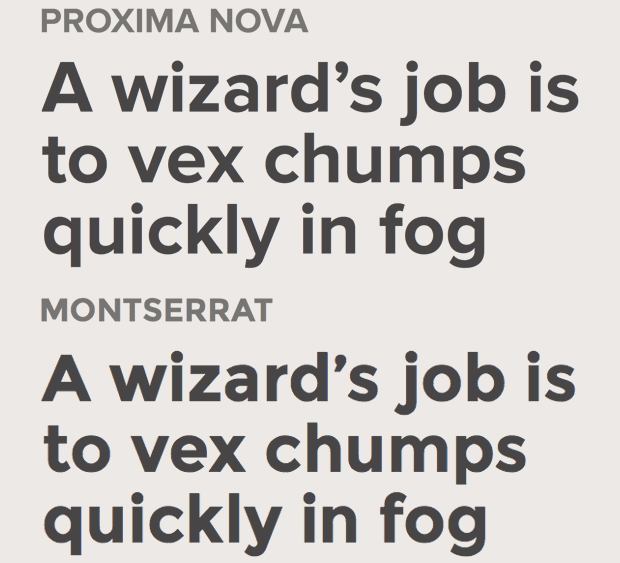
С момента своего релиза 10 лет назад шрифт Proxima Nova занял лидирующие позиции. Для тех, у кого нет этого шрифта, может подойти Montserrat – бесплатный геометрический шрифт с очень похожими характеристиками. Он хорошо смотрится в верхнем регистре (заглавными буквами).
2. Josefin Sans вместо Futura
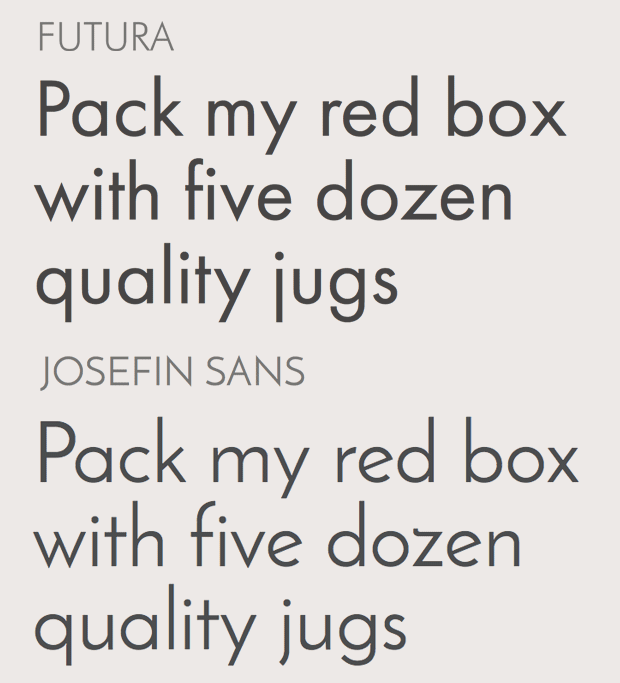
Futura – любимый геометрический шрифт каждого, кто знаком с его острыми углами. Как бесплатная альтернатива может подойти Josefin Sans – чистый геометрический шрифт. Формы символов этих шрифтов практически идентичны. Разница менее заметна при использовании верхнего регистра.
3. Roboto вместо FF DIN
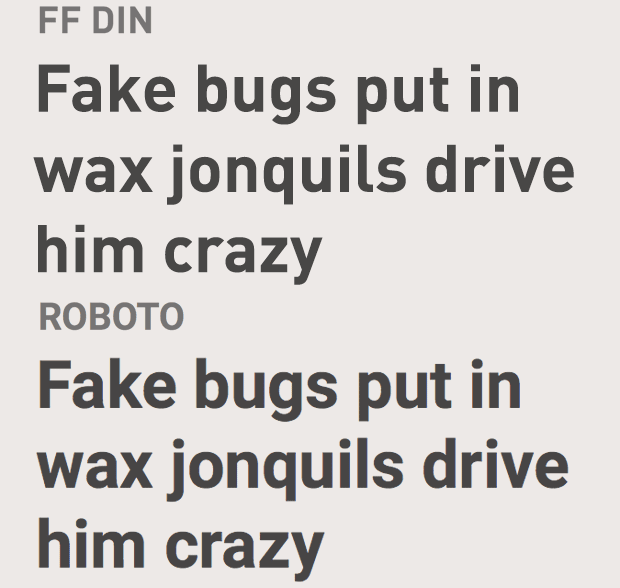
Roboto – лучшая альтернатива популярному шрифту FF DIN. Многие символы этих шрифтов совпадают как в нижнем, так и в верхнем регистре, а наличие стилей даст возможность использовать Roboto вместо всех вариантов FF DIN.
4. Bitter вместо FF Tisa
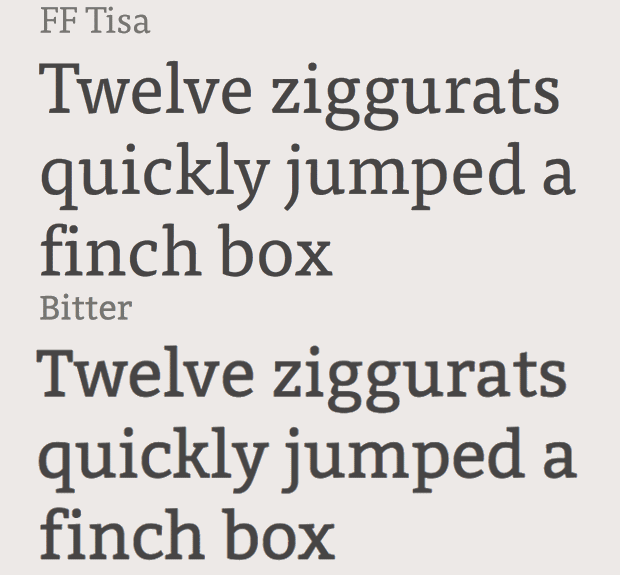
FF Tisa – популярный шрифт с изогнутыми линиями засечек. Похожие элементы также есть у Bitter – бесплатного шрифта, который способен заменить популярный вариант.
5. Merriweather Sans вместо FF Meta
Может показаться, сложно найти похожий шрифт для FF Meta, но Merriweather Sans хорошо справляется с этой задачей.
6. Libre Baskerville вместо Baskerville
Baskerville – один из самых популярных классических шрифтов с засечками, на основе которого существует бесплатный шрифт Libre Baskerville. Для самого лучшего восприятия рекомендуется снизить контрастность шрифта, а стандартный вид очень сильно похож на жирное начертание Baskerville.
7. Ultra вместо Clarendon
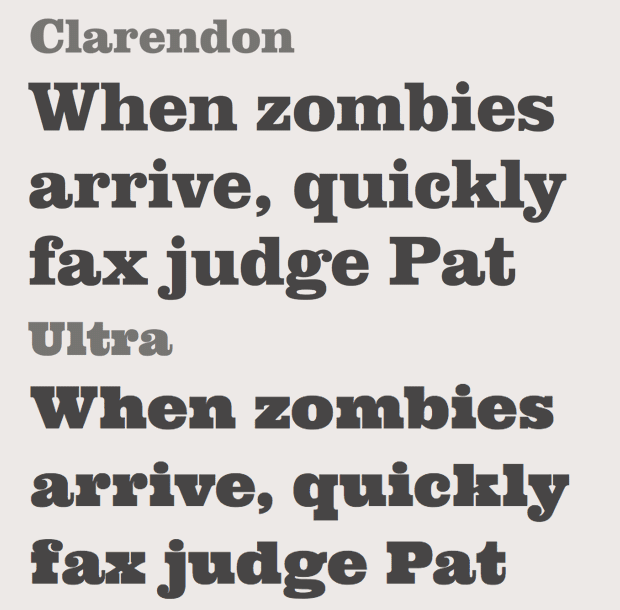
Шрифт Clarendon имеет значимый вес и жирное начертание. Хорошей альтернативой может стать Ultra – шрифт с выраженными засечками-платформами.
8. Work Sans вместо Helvetica Neue
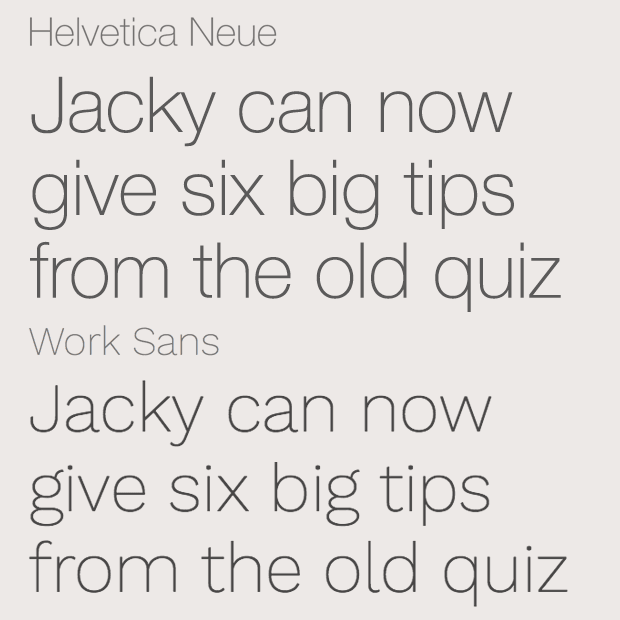
В то время как Clarendo часто используется в варианте Black, Helvetica Neue почти всегда применяют в варианте Light или Ultra Light. Этот шрифт часто скачивают и используют неправомерно, хотя имеется хорошая альтернатива – Work Sans.
9. Abril Fatface вместо Bodoni Poster
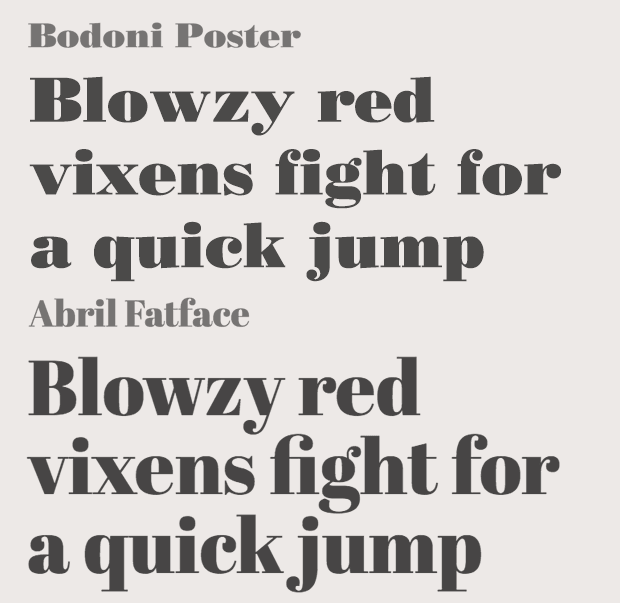
Хотя здесь сравнивается Bodoni Poster, его бесплатная альтернатива Abril Fatface может быть заменой большинству современных стилей Didone.
10. Hind вместо Frutiger
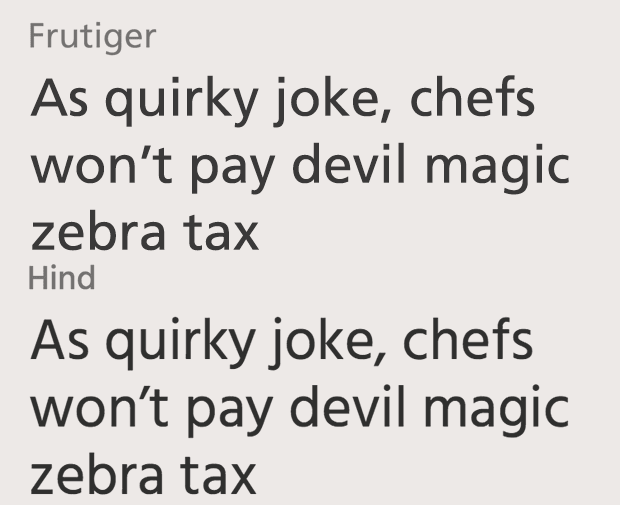
Frutiger – шрифт без засечек с аккуратными буквами, который хорошо подходит для использования как в больших вывесках, так и постерах. Бесплатный шрифт Hind является идеальной альтернативой с максимальным соответствием символов.
11. Lato вместо Brandon Grotesque
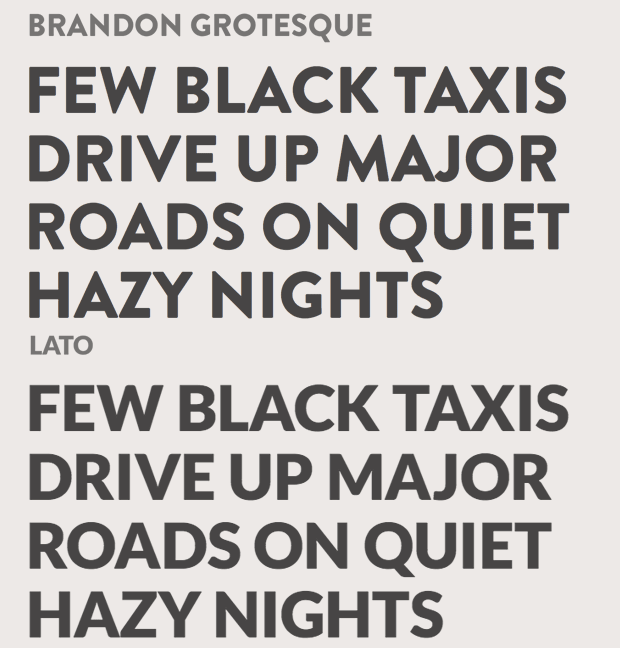
Lato может стать хорошим вариантом использования вместо популярного гротескного шрифта Brandon Grotesque.